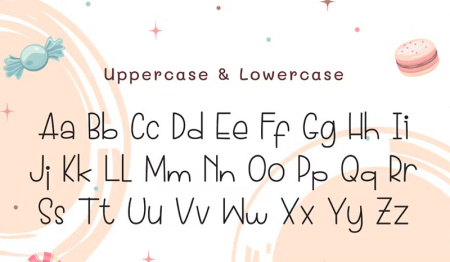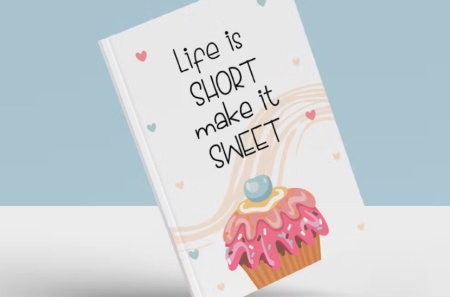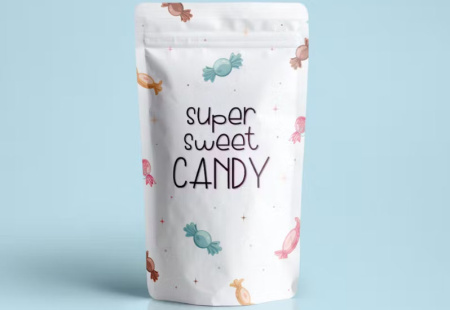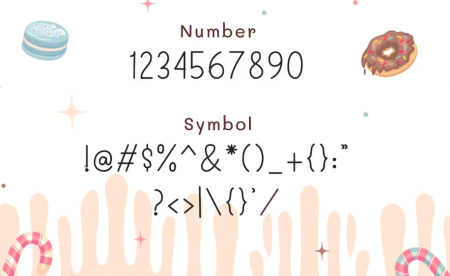
دانلود رایگان فونت انگلیسی Donut Candy
دانلود رایگان فونت انگلیسی Donut Candy که به صورت کاملا رایگان از سایت gfx برای دانلود در اختیار شما قرار داده است. فونت نمایشی بازیگوش و زیبا، تک تک حروف با دقت ساخته شده اند تا متن شما زیبا به نظر برسد. با سبک منحصر به فرد مدرن، این فونت برای بسیاری از پروژه های مختلف مانند نقل قول، سربرگ وبلاگ، پوستر، عروسی، برندسازی، آرم، مد، پوشاک، نامه، دعوت نامه، لوازم التحریر و غیره عالی خواهد بود.